本記事では、キュンとくる♡「恋愛系」にぴったりの日本語フォントをまとめてみました。
告白シーン、ラブレター、恋愛ゲーム、恋をテーマにしたデザイン──そんなときに欠かせないのが、甘くてときめく雰囲気を演出してくれるフォントです。ふわっとした手書き感や、ハートを感じさせる丸みのあるフォルム、ちょっぴり切なさを漂わせる繊細な文字など、恋の世界観を引き立ててくれる要素が満載です。
今回は、恋愛をテーマにしたデザインにぴったりな、日本語フリーフォントを厳選しました。恋する気持ちを表現したいとき、心を動かす演出をしたいときに、ぜひ活用してみてください。
「恋愛系」におすすめのフリーフォントのまとめ
夏蝉丸ゴシックフォント
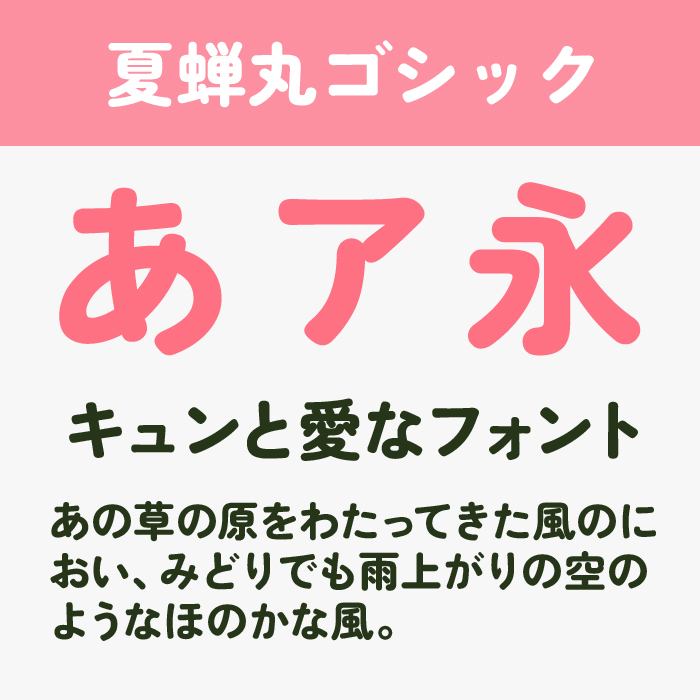
夏蝉丸ゴシックフォントは、素朴さと甘さが心地よく混ざり合った印象のフォントです。丸みのある骨格に、ほんのり切なさを感じる線のゆらぎが加わり、夏の思い出や淡くてやさしい恋のシーンにぴったりな雰囲気を演出してくれます。
あめちゃん
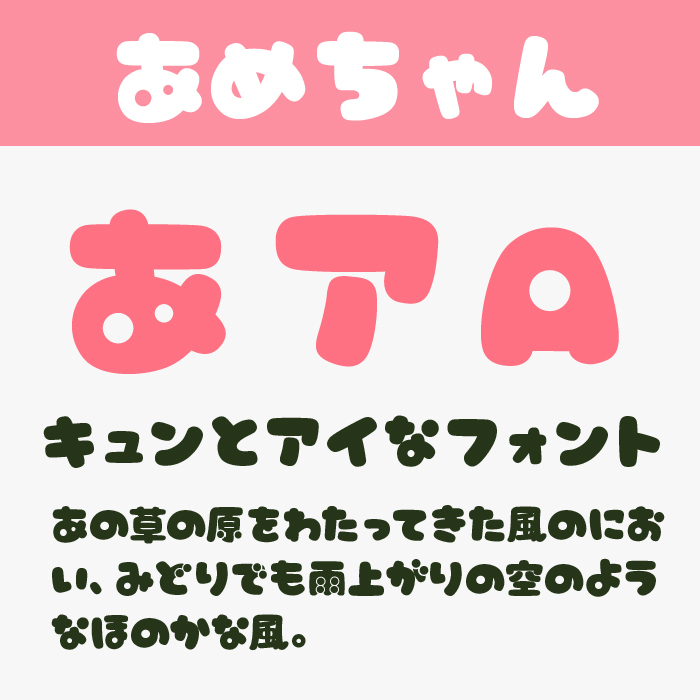
あめちゃんフォントは、まるで飴細工のようにぷっくりとした形が印象的で、見ているだけで胸がときめくような可愛さがあります。無邪気さや素直な気持ちを伝える恋愛表現にぴったりな、あどけなさを感じさせるフォントです。
ふてほど丸ゴシック
ふてほど丸ゴシックフォントは、ゆるっとしたバランスと程よい太さが特徴で、ナチュラルな可愛らしさをもつフォントです。押しつけがましくなく、それでいて愛嬌があるので、淡い恋心や日常のときめきをやさしく表現できます。
まきばフォント
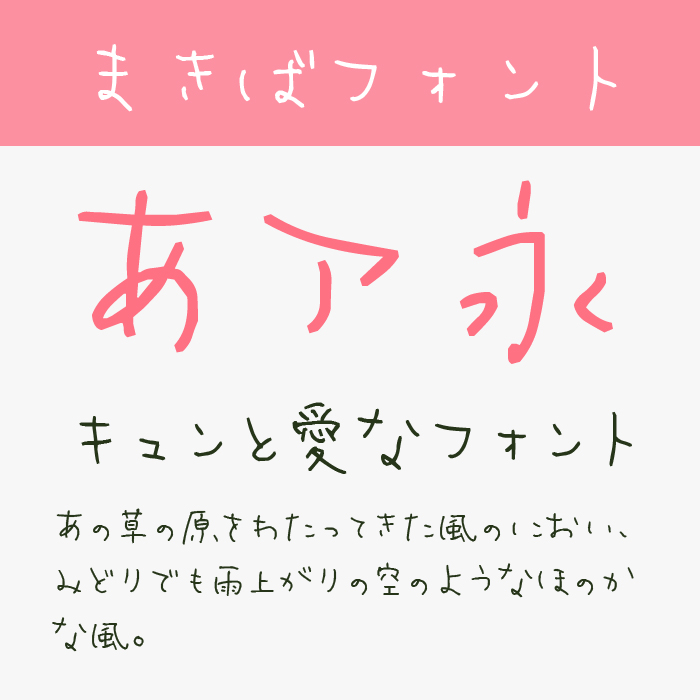
まきばフォントは、筆跡のような線の揺らぎが特徴で、繊細で儚い恋の感情を静かに伝えるような雰囲気があります。等身大の想いをナチュラルに描き出すような手書き感があり、告白シーンや手紙風デザインにぴったりです。
ブルズドーナツフォント
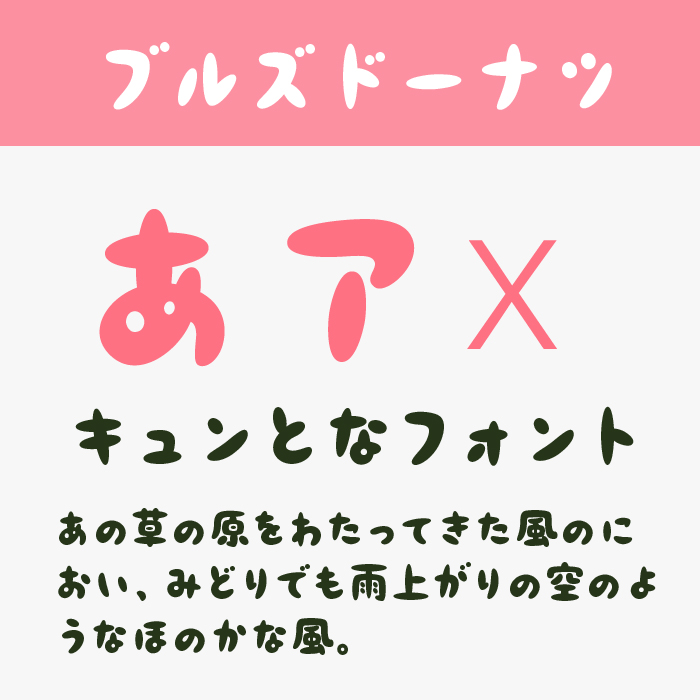
ブルズドーナツフォントは、コロンとした形とやや太めのボリューム感が魅力で、ポップな恋愛の世界観をぐっと引き寄せてくれるフォントです。明るくて甘い恋模様や、元気いっぱいのキャラクターに合う、愛らしさ満点のフォントです。
モッチーポップフォント
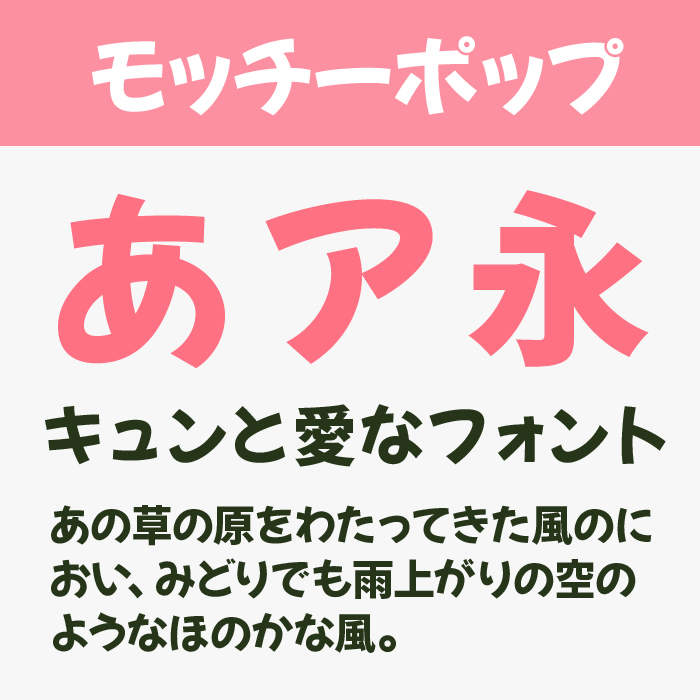
モッチーポップフォントは、もちっと弾力のある印象と安定した丸みで、親しみやすさと安心感を備えた可愛いフォントです。恋のときめきを素直に届けたいときや、ほっこりとした気持ちを表現したいときにおすすめです。
黒薔薇ゴシック
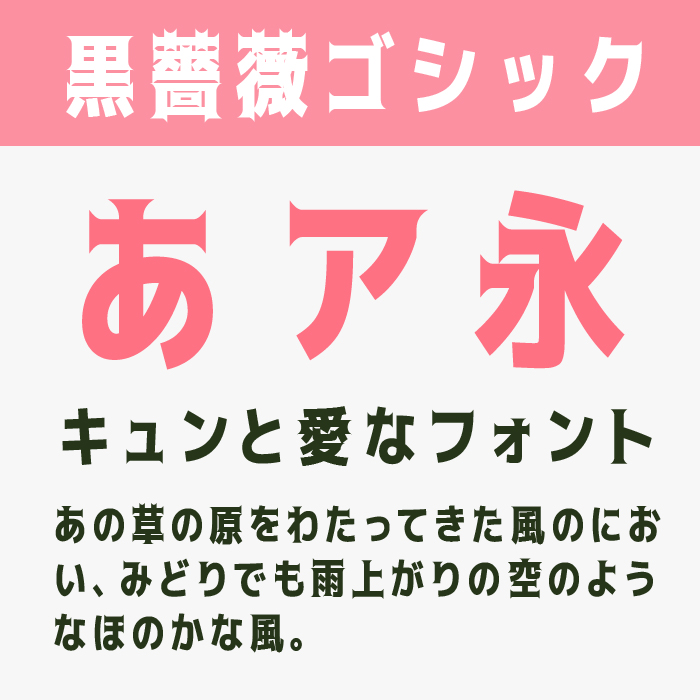
黒薔薇ゴシックフォントは、スリムで繊細な線の中に華やかな装飾が施されており、ドラマチックでロマンチックな雰囲気が漂うフォントです。切なさや情熱を秘めた恋愛表現を、美しく際立たせてくれるフォントです。
天浜線フォント
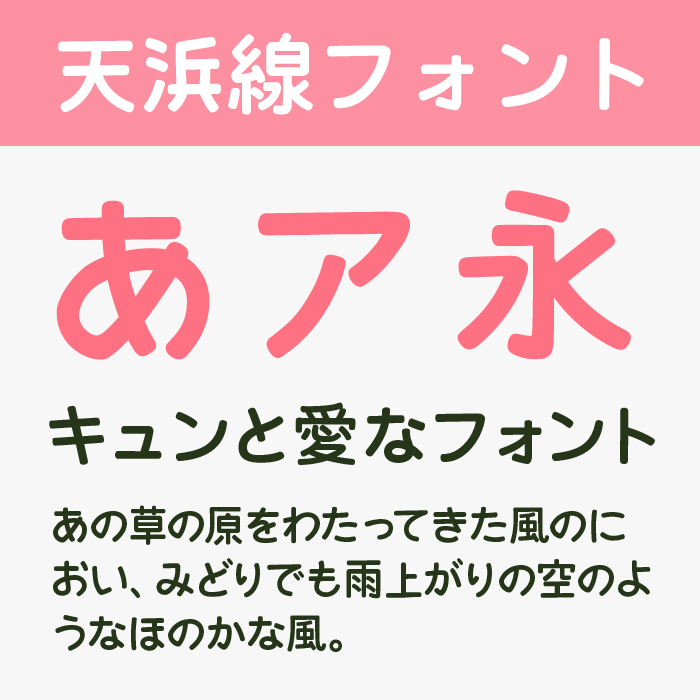
天浜線フォントは、ふわっとした筆跡とリズム感が特徴で、柔らかい手描きの温度を感じられる優しいフォントです。自然体な恋愛や、気取らないやりとりを描いた作品に合う、親しみのあるタッチが魅力です。
えるまーフォント
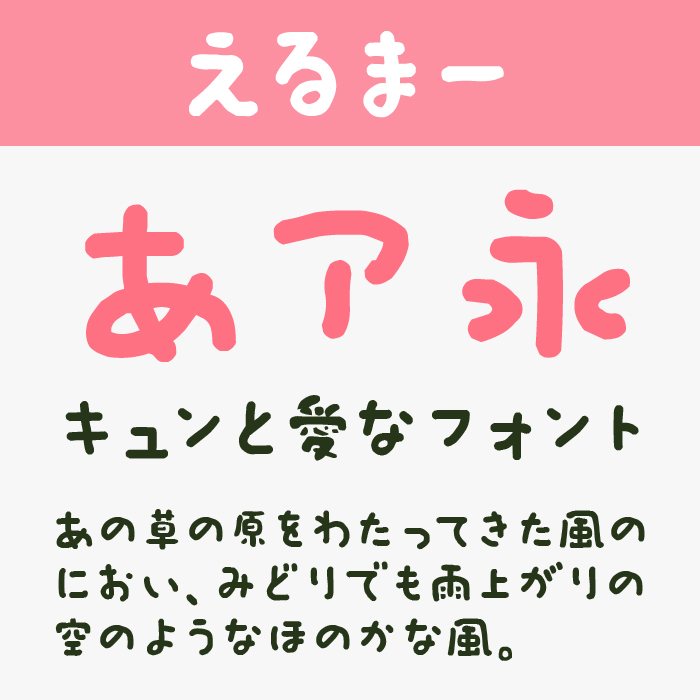
えるまーフォントは、やさしい丸みと手書きらしさが合わさり、温もりのあるやわらかな恋の気持ちを表現できるフォントです。素直な気持ちやナチュラルな愛情を込めたメッセージに最適な、日常に寄り添うフォントです。
はる手書きフォント
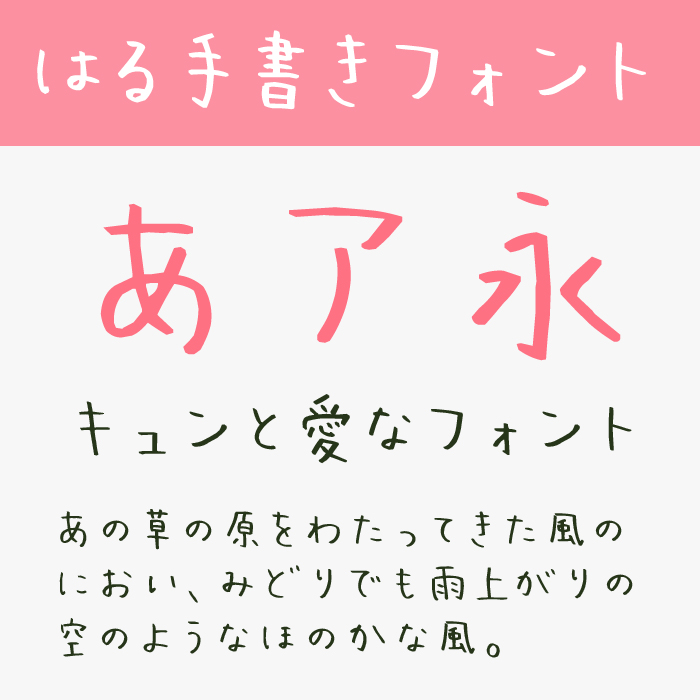
はる手書きフォントは、筆跡の軽やかさと素朴な線が印象的で、等身大の恋心を静かに語るような雰囲気が魅力なフォントです。飾らないまっすぐな想いを伝えるシーンや、繊細な表現が求められる恋愛系デザインに向いています。
バナナスリップフォント
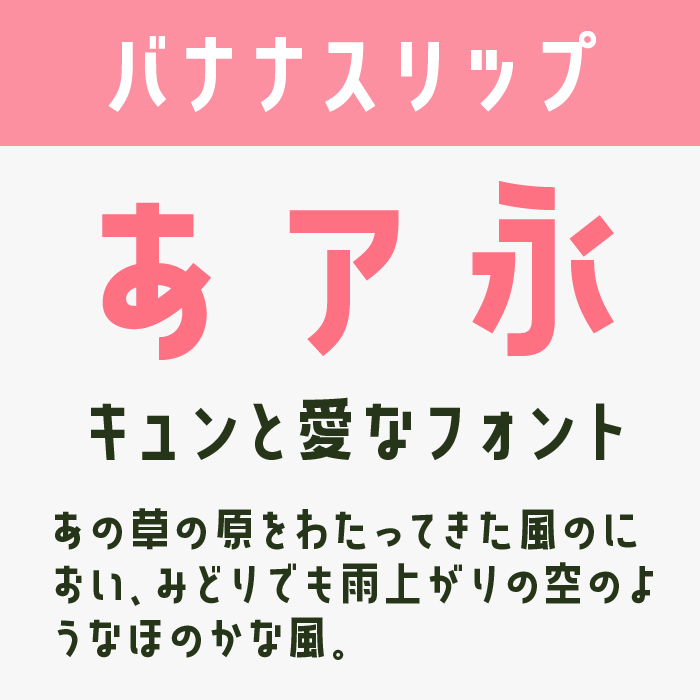
バナナスリップフォントは、長体でクセになる丸みと、程よく引き締まった長体のシルエットが絶妙なバランスなフォントです。ラブコメやポップな恋愛テーマにぴったりで、ちょっと照れくさいセリフにも自然と馴染む、可愛げと遊び心があるフォントです。